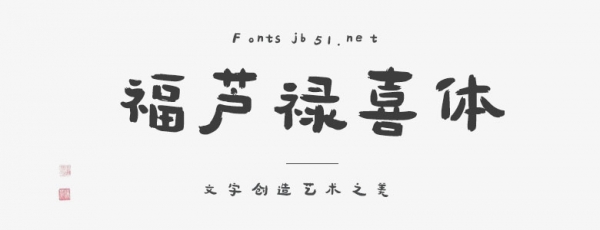
字體以 “筆觸感” 為基底,通過強(qiáng)化毛筆書寫的自然痕跡,展現(xiàn)墨色濃淡交織。融入童趣化表達(dá),以圓潤萌動的線條、活潑俏皮的字形結(jié)構(gòu),打破傳統(tǒng)書法的規(guī)整束縛,賦予字體天真自由的視覺性格。將傳統(tǒng)書法韻味與現(xiàn)代時尚審美融合,輕松隨性的筆畫銜接,打造兼具文化底蘊(yùn)與潮流感的視覺形態(tài),既傳遞書法藝術(shù)的靈動之美,又適配個性化的時尚場景,實(shí)現(xiàn)傳統(tǒng)與潮流的創(chuàng)意碰撞。